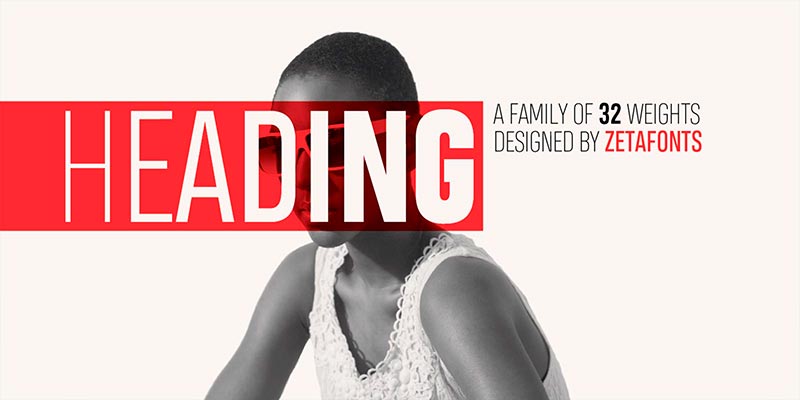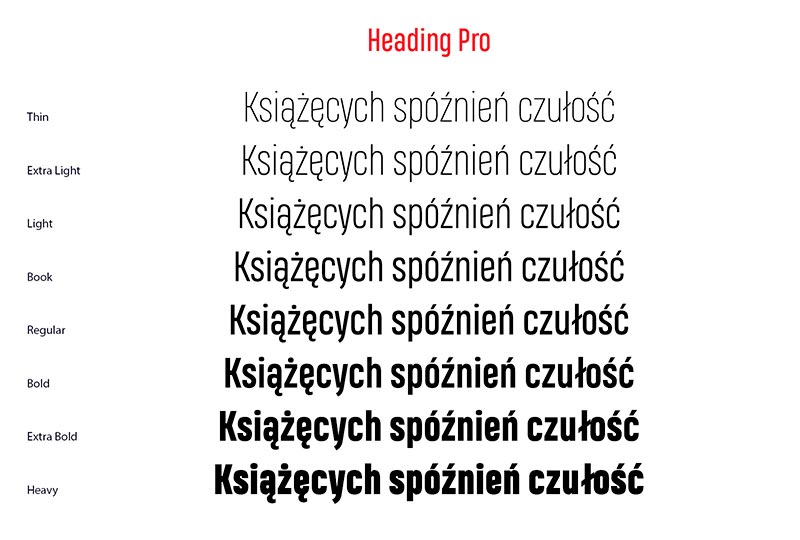
Font Heading Pro
Do kolekcji naszych fontów trafił Heading Pro. Oprócz wersji podstawowej ma też skondensowaną, co czyni go idealnym do stosowania w nagłówkach gazet.